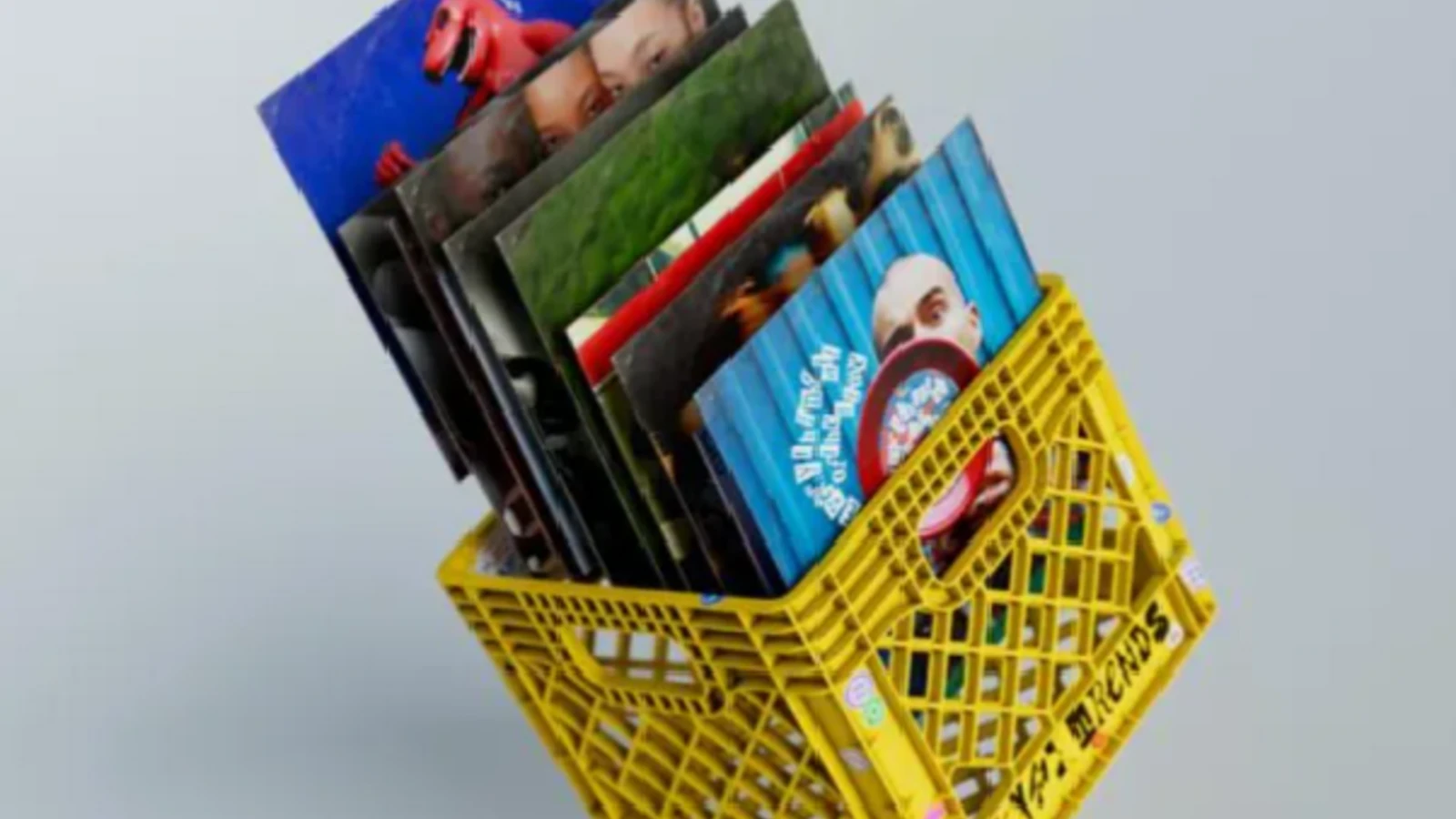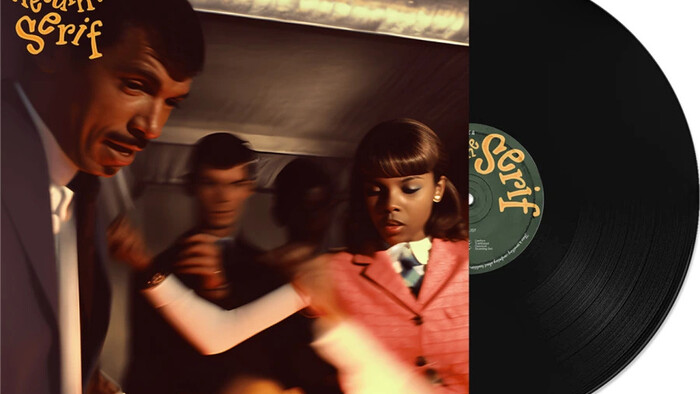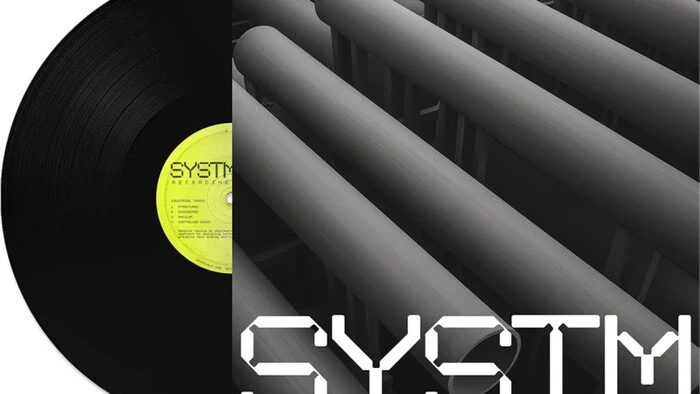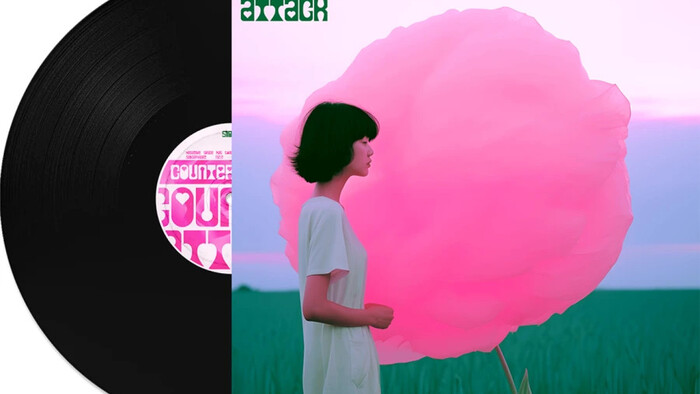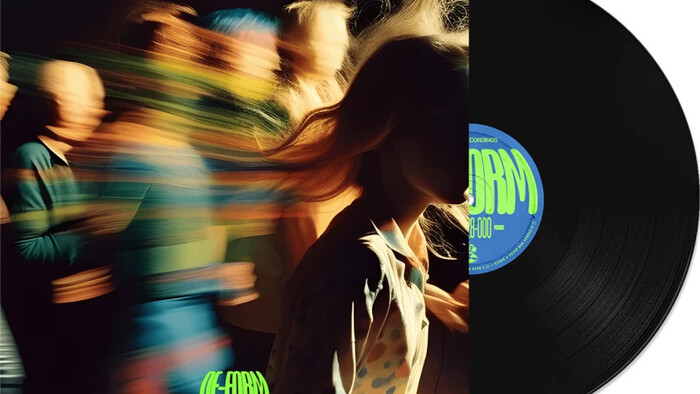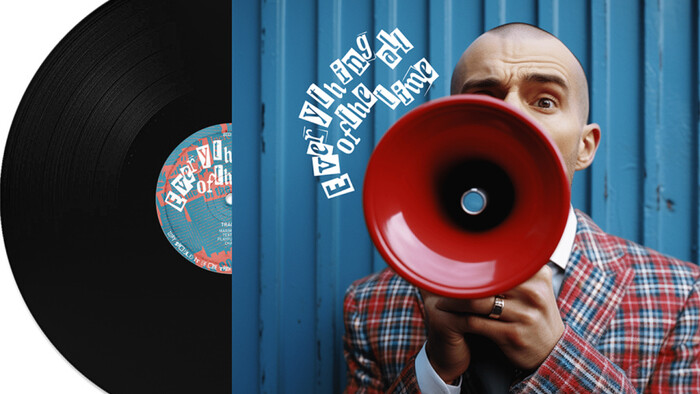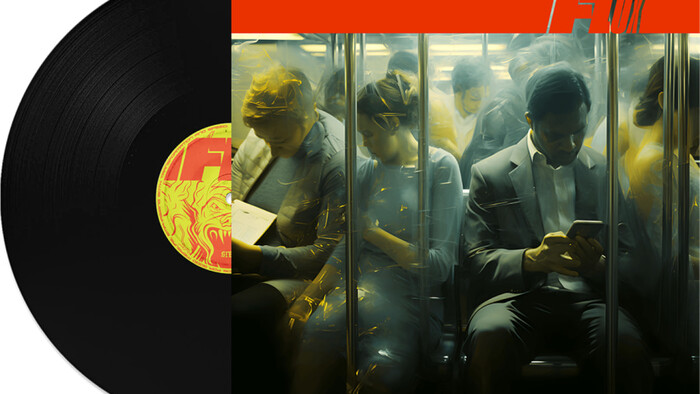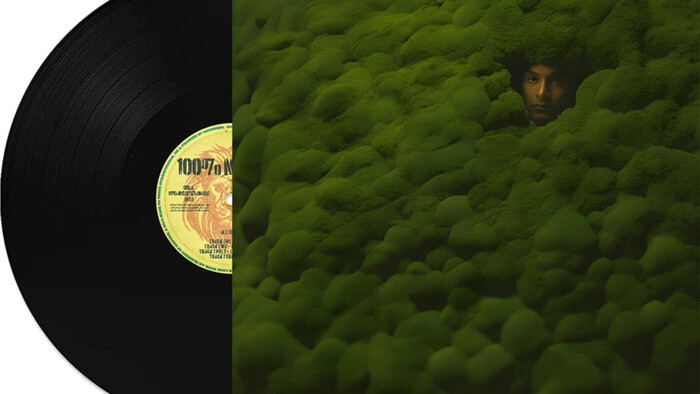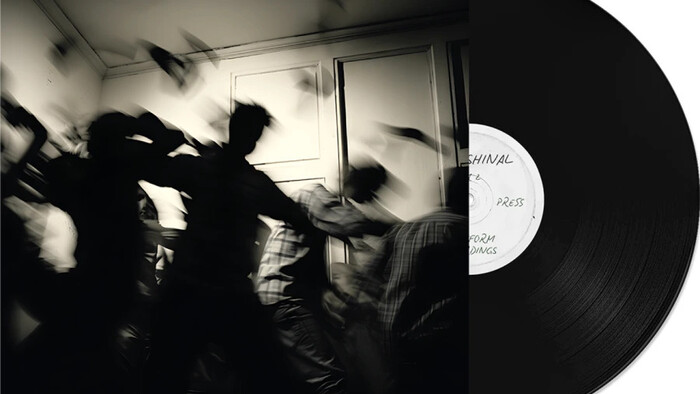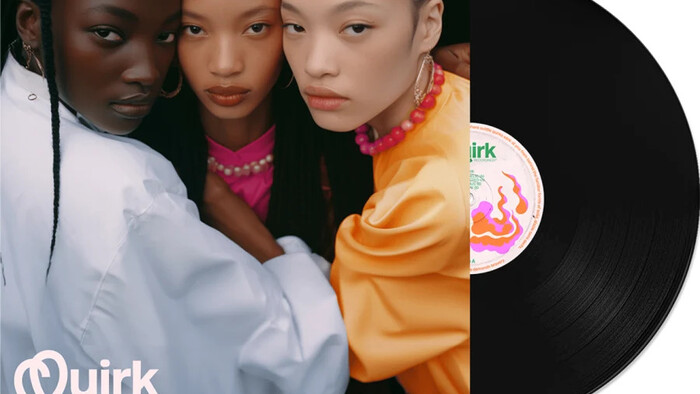
Type Trends 2024.
Schrift erzählt uns was, die ganze Zeit.
Unser jährlicher Type Trends Report ist ein feierliches Ritual und zugleich die Gelegenheit, einige der typografischen Vordenkerinnen und Vordenker zu ehren, die uns weltweit begeistern. Es ist aber auch der Anlass zur Selbstreflexion: Was sagen die Arbeiten über uns selbst aus, was bewirkt das Schaffen der Kreativen und warum ist es für uns relevant?
Everythingallofthetime.
Wenn Schrift etwas über das heutige Leben aussagt, dann spiegelt dieser erste Trend gleich mehrere Facetten unseres aktuellen Befindens wider: überall und alles auf einmal.
Whatever.
Der aus der 90er-Jahre-Nostalgie geborene Whatever-Trend umfasst ein Spektrum von Stilen, das vom nihilistischen Grunge bis zu bunten Pixelspielereien reicht.
Systm.
Trotz der technischen Arbeitsweise des Schriftdesigns fühlen sich Systm-Projekte überraschend analog und von Menschenhand gemacht an.
De-form.
Ist das jetzt der beste variable Font aller Zeiten, oder nur eine Verzerrung?
Flux.
Ob tatsächlich animiert oder von Bewegungen inspiriert: Flux strahlt Tempo und Dynamik aus.
Quirk.
Die Bereitschaft, etwas Unerwartetes auszuprobieren, sich abzuheben, anders zu sprechen.
Counter Attack.
Der negative Raum tritt in den Vordergrund und kämpft dafür, gesehen und gefeiert zu werden.
Profeshinal.
Eine raffinierte Mischung aus Humor und Ehrlichkeit, die zu sonderbaren, aber brillanten Kreation führt.
100% Natural.
Wenn die Freude am Schriftmachen Überhand nimmt und Wörter mit einer nachhaltigen Denkweise strategisch positioniert werden.
Return of the Serif.
Tradition hat etwas Beruhigendes, sie gibt uns Halt in einem immer komplexeren Umfeld.